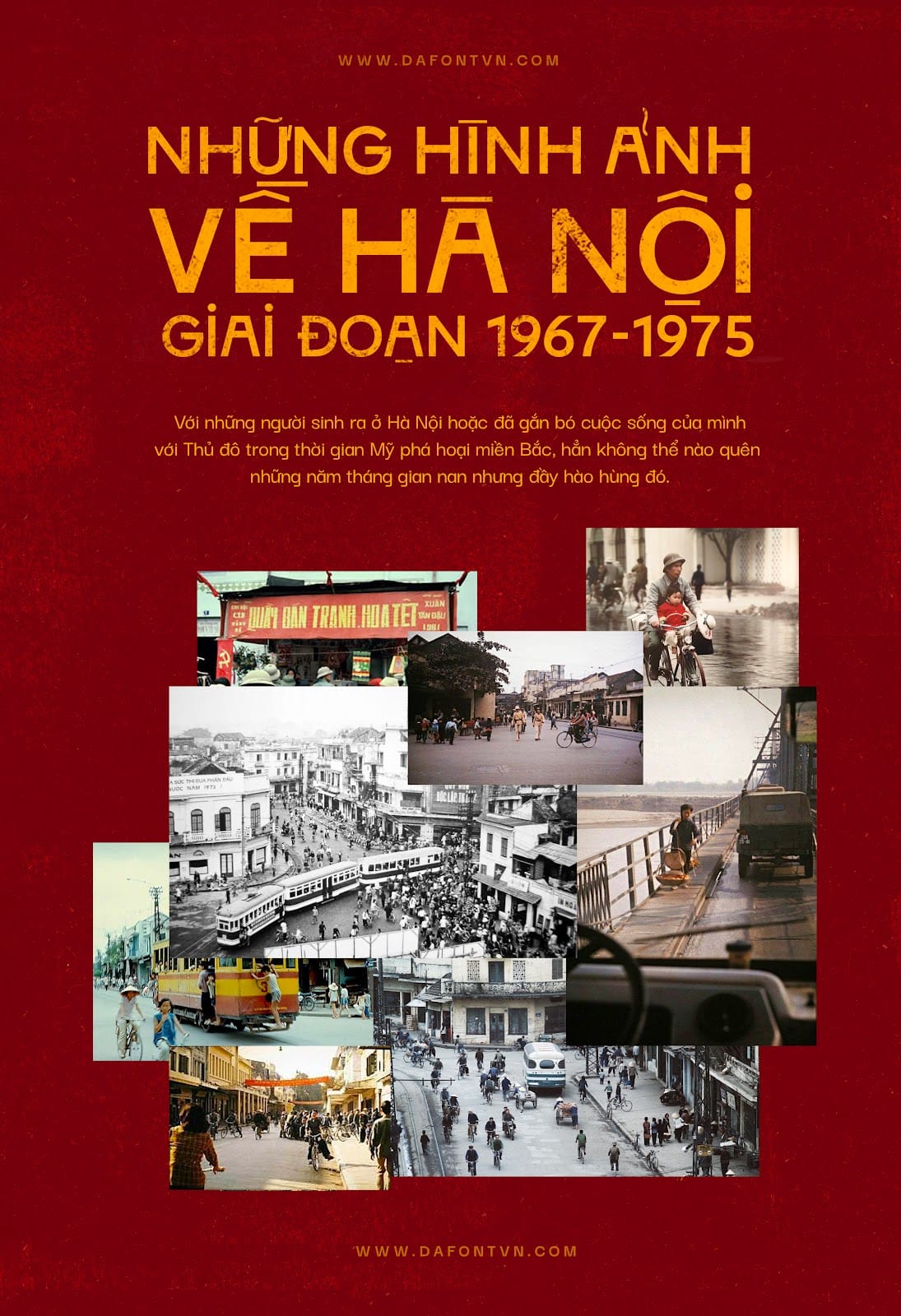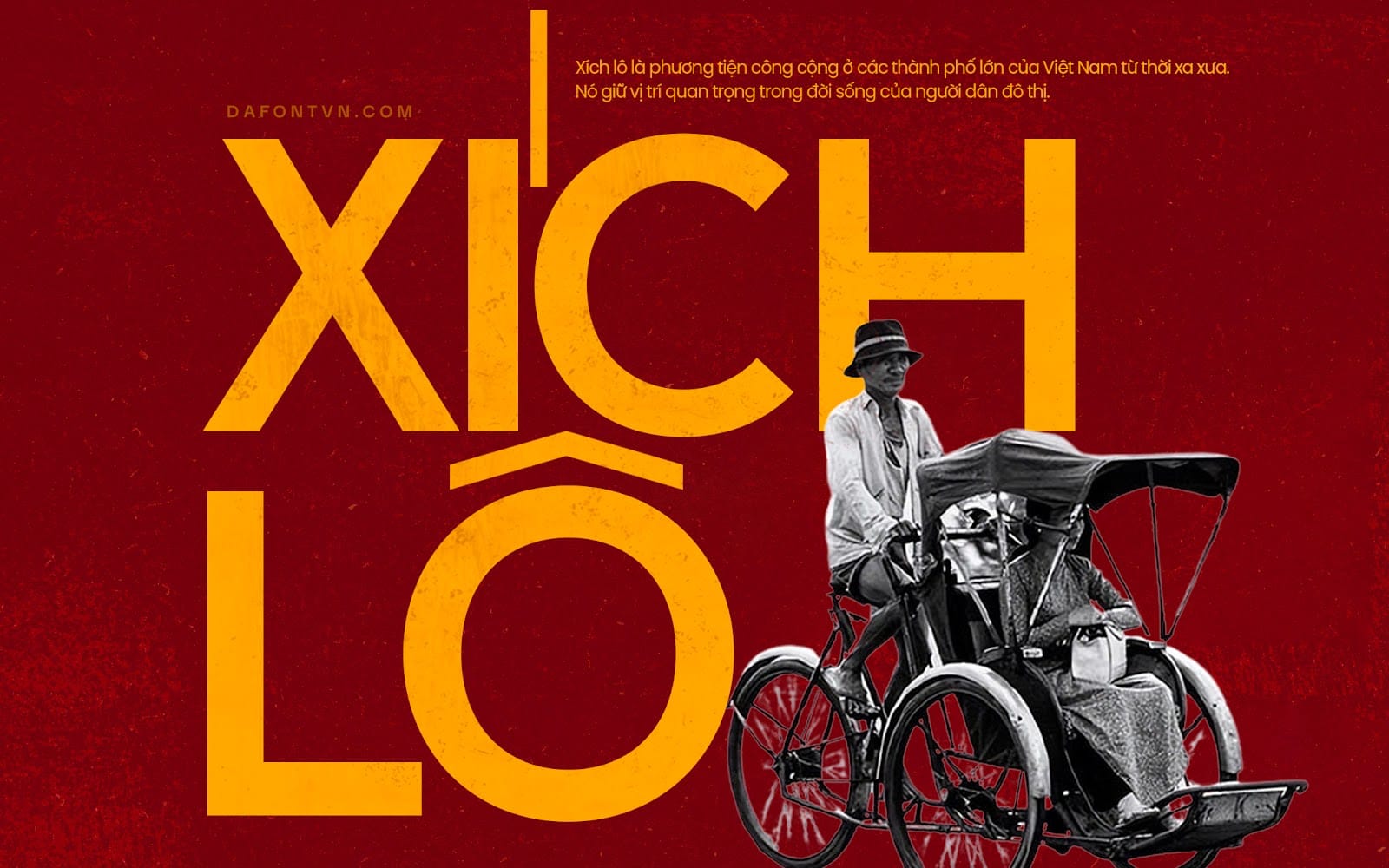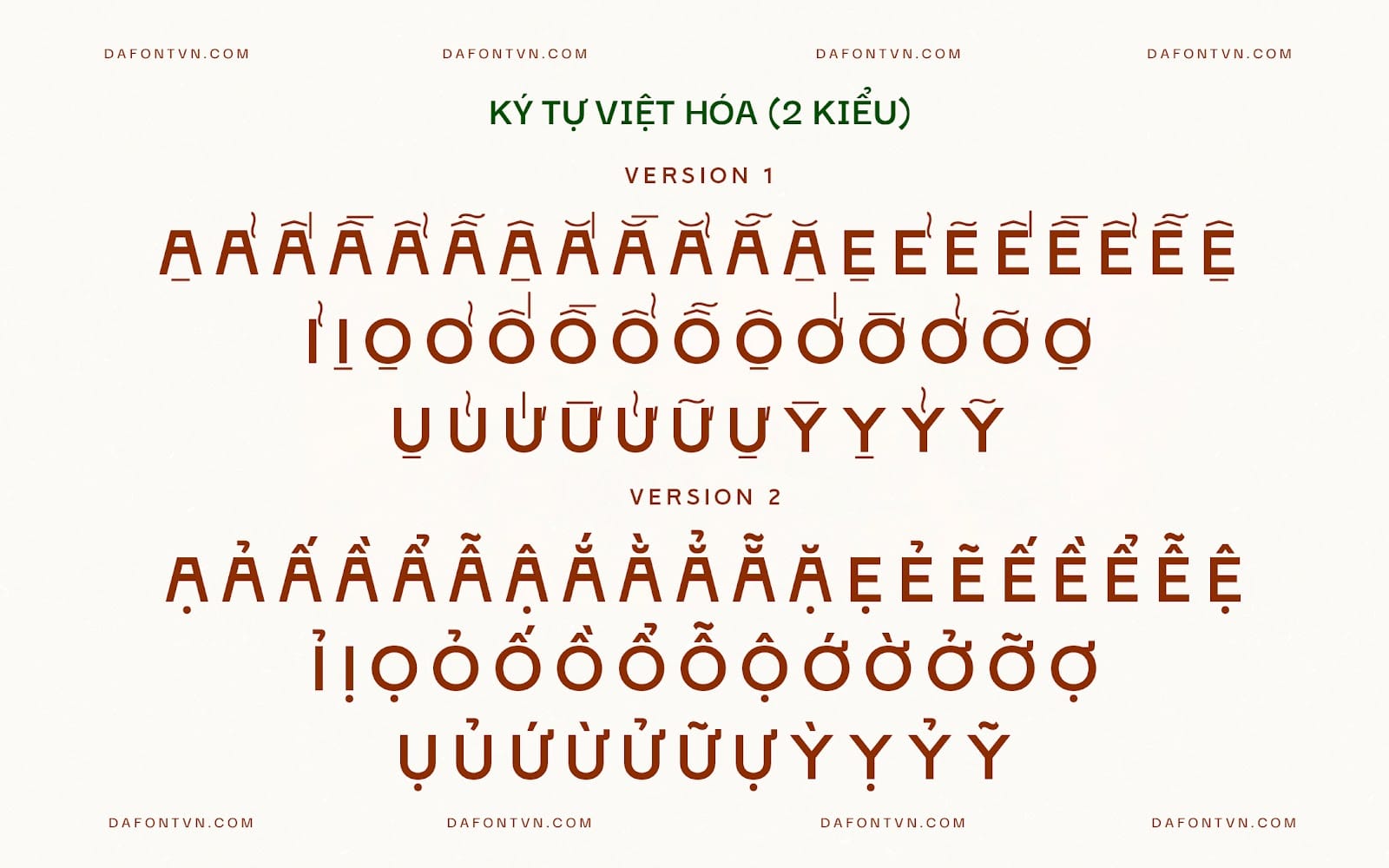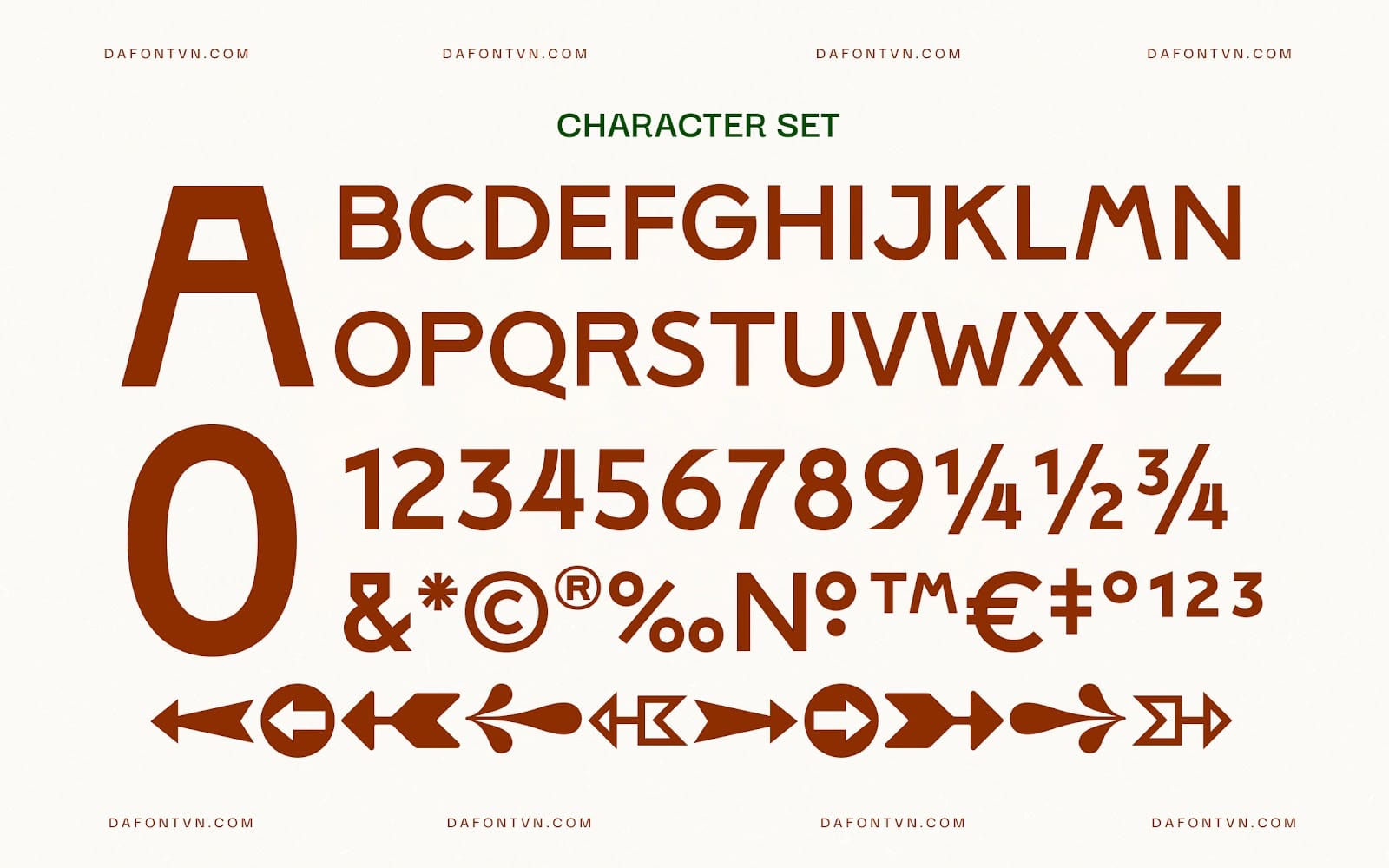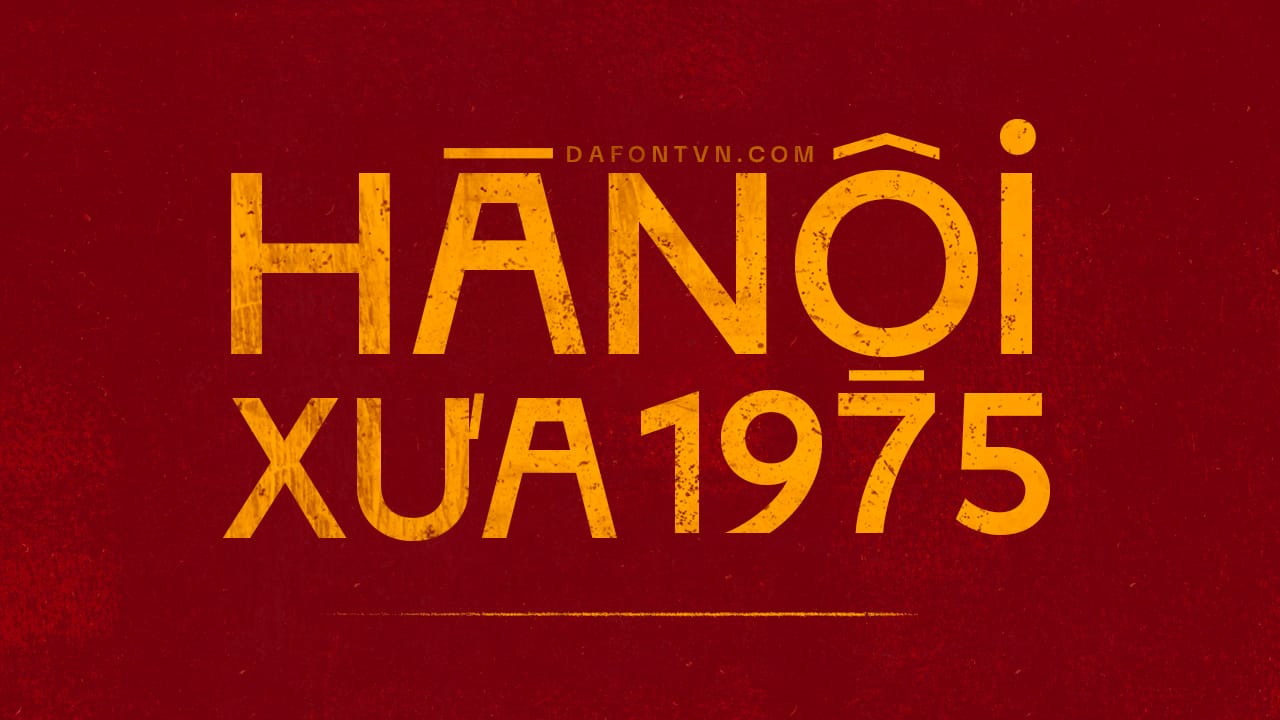
Stampa Font là kiểu chữ san serif được lấy cảm hứng từ La Stampa – đây là một tờ nhật báo của Ý được xuất bản tại Turin, nó là một trong những tờ báo lâu đời nhất ở Ý. Vì vậy font chữ được việt hóa mang phong cách xưa cũ thời bao cấp.
Font phù hợp cho nhiều thiết kế như tiêu đề, logo, áp phích, nhãn hiệu, tạp chí, bao bì…Ngoài ra font được việt hóa với 2 kiểu dấu khác nhau để bạn có thể dễ dàng sử dụng kiểu chữ này cho nhiều thiết kế khác nhau, bạn có thể xem bộ dấu ở ảnh demo bên dưới.